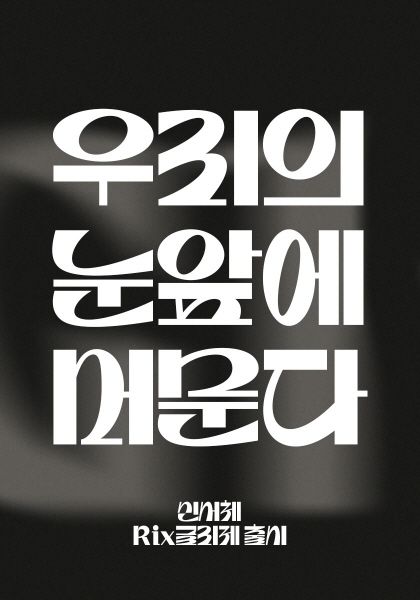
선의 조형미와 자소의 형태미가 돋보이는 제목용 서체
폰트 서비스 플랫폼 '릭스폰트'(RixFont)는 곡선과 직선의 대비를 통해 조형적 리듬감을 극대화한 'Rix글리제'를 출시했다고 20일 밝혔다.
'Rix글리제'는 유연한 곡선과 직선의 강렬한 대비, 그리고 자소(字素)의 독창적인 형태미를 특징으로 하는 제목용 서체다. 특히 ㄹ, ㅌ, ㅈ 등의 자소에는 숫자 '3'을 연상시키는 곡선적 형태를 적용해 서체 전반에 리듬감과 시각적 즐거움을 더했다.
글자 하나하나가 시선을 사로잡는 포인트가 되어 브랜드 타이틀, 광고 헤드라인 등 주목성을 요구하는 영역에서 효과적으로 활용할 수 있다. 글자 자체가 시각적 아이덴티티의 중심이 되는 디자인 환경에서 'Rix글리제'는 차별화된 형태감으로 독창적인 표현력을 발휘할 것으로 예상된다.
'Rix글리제'를 제작한 유현주 폰트 디자이너는 "시각적으로 재밌고 독특한 디자인의 서체를 만들고 싶다는 생각에서 시작했다. 작업 초기 키워드로 '유성의 꼬리'를 떠올렸고, 별빛의 흐름과 유성의 궤적처럼 글자마다 리드미컬한 흐름을 담고자 했다"고 말했다. 이어 "곡선과 직선이 만나는 순간의 리듬을 세밀하게 조형해 글자 자체에 움직임을 부여하고 싶었다"며 "글자를 단순한 읽기 수단이 아닌 시각적 조형물로서 활용할 수 있도록 서체 디자인의 경계를 넓히는 실험을 계속해 나가고 싶다"고 밝혔다.